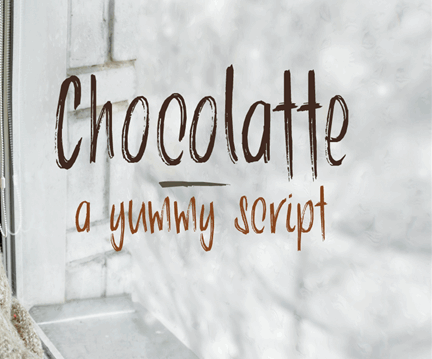
DK Chocolatte Font – Download Grátis
A fonte ‘DK Chocolatte Font’ é uma seleção elegante de traços delicados e suaves, projetada para quem busca uma fonte com características que lembram o sabor do chocolate ao amanhecer — sempre presente mas nunca excessivamente forte. Esta fonte Brush Fonts, criada pelo designer David Kerkhoff, oferece um toque refinado que se adequa perfeitamente a qualquer projeto de design gráfico, particularmente para editoriais e interfaces digitais. Para usar esta fonte em uma escala comercial, entretanto, é necessário ter o versão completa com recursos adicionais como kernenção, direitos de embedding e extras exclusivos disponíveis apenas no site do designer. Não use a fonte em jogos, aplicativos ou software — ela está reservada para ambientes mais formais e elegantes que elevam seu design gráfico ao próximo nível. Se deseja adquirir um licenciamento, visite o site de David Kerkhoff: www.hanodedfonts.com, onde você encontrará todos os detalhes necessários.